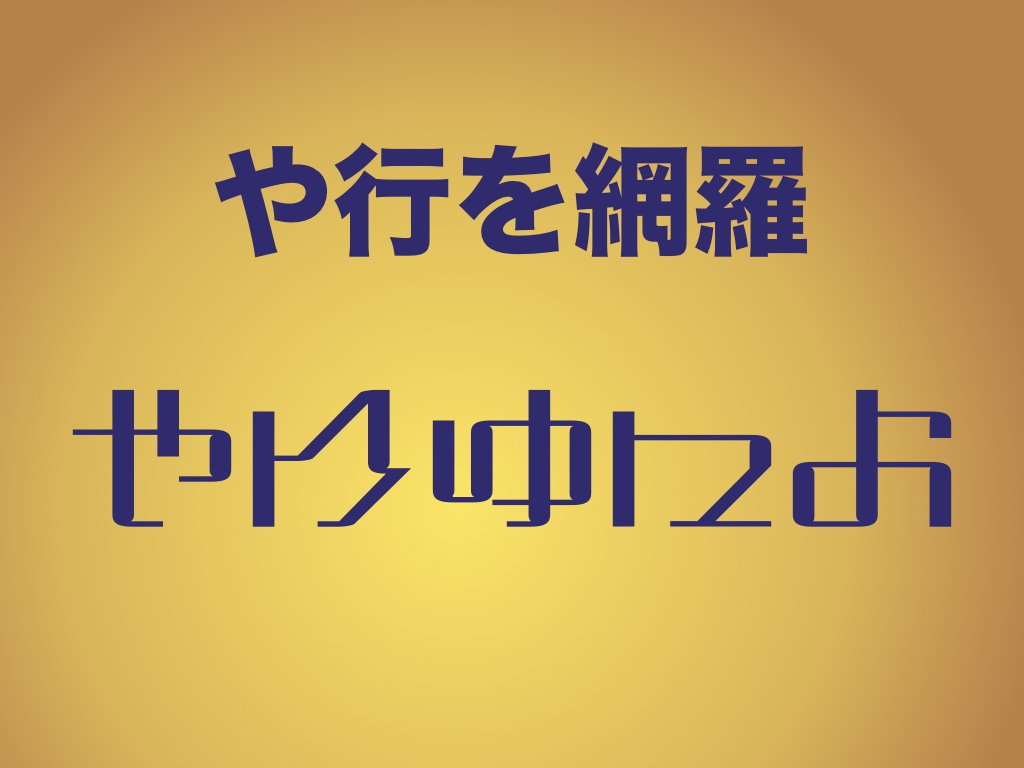
フリーのひらがなフォント BOTERIN
新作フリーフォント「異端仮名『怪』」登場!ぜひご利用ください! https://fontring.booth.pm/items/3213962 フリーのひらがなフォント「BOTERIN」です。ぼってりとした可愛い見た目ながら、どこか未来感もある楽しいフォントです。 無料で私用から商用まで幅広い用途にご利用いただけます。ゐやゑなどのひらがなはもちろん、「や行い」「や行え」も備えています。 LINE絵文字においての使用は、条件付きで許諾します。詳しくはzip内のReadMeをご覧ください。 ⚠️投げ銭用のバージョンは無料のバージョンと全く同一のものが入っています。 投げ銭を検討される方は、下記のフォントをご購入くださいますことも大変励みになります。 ・欧文/カタカナフォント CORORIN https://fontring.booth.pm/items/871969 ・欧文フォント Lemonin https://fontring.booth.pm/items/1156944 作ったフォントが使われているのを見るのが好きです。作品を投稿する際にタグ「#ぼてりん」を付けたりクレジットに記載したりしていただくと見つけやすいので嬉しいです😉 このフォントを紹介される際、Boothのサンプル画像は自由にご利用ください。 フォントのバージョンアップのお知らせはこちらで投稿します。フォローお願いします🙏 https://www.pixiv.net/fanbox/creator/31276656